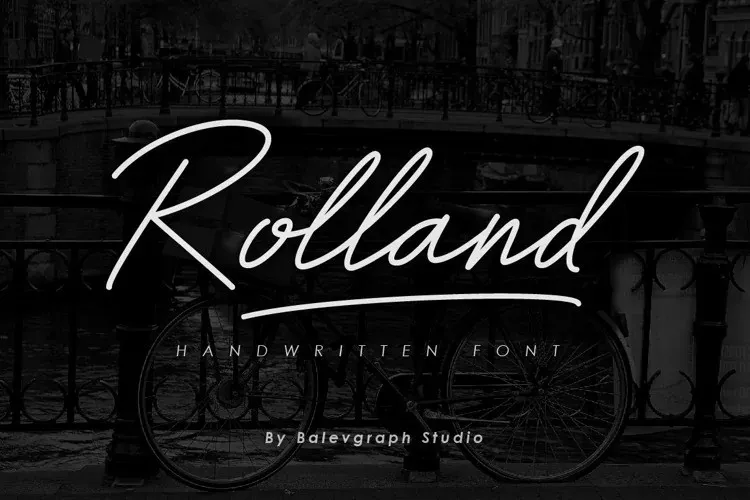
Rolland Font – Download Grátis
A Rolland Font é uma moderna tipografia monoline script criada pela Balevgraph Studio. Com seu estilo fresco e elegante, ela parece perfeita para qualquer projeto que você esteja planejando. Essa fonte será uma ótima escolha para adicionar um toque alegre e romântico às suas ideias de design. Ela é ideal tanto para aplicações digitais quanto impressivas em papel, tornando-a uma ferramenta valiosa para designers buscando um equilíbrio entre simplicidade e sofisticação. Uma fonte que valoriza a delicadeza e a pureza, pode transformar qualquer projeto em algo realmente especial. Experimente Rolland Font na 99designs hoje e veja como ela pode fazer a diferença no seu próximo trabalho.